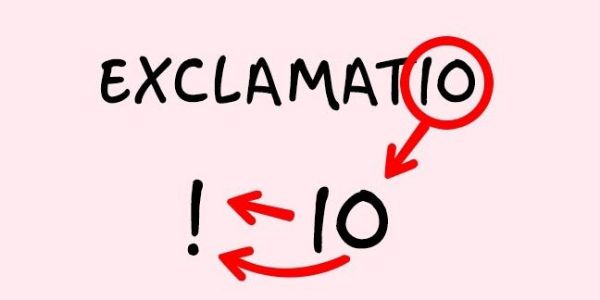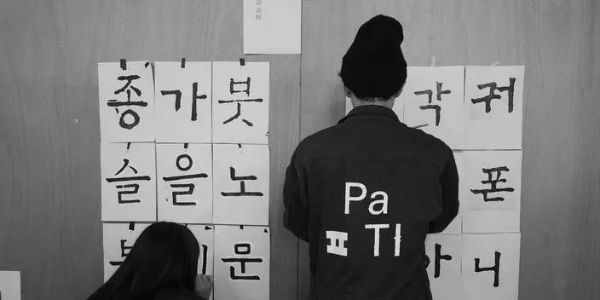
为什么要学字体设计?
为什么要学习字体设计?开年以来还是陆陆续续收到部分字友问的这个问题。今天再和大家分享一下。
不难看出,随着大众审美的不断提高,大家对设计感的追求变得不可或缺,使得“字体”在视觉传达设计中有了一个必要存在的趋势。
在讨论字体设计时,我们先要分清楚字体和字库设计的区别。
字库的设计更多需要注重大范围的可阅读性、辨识性、统一性、推广性,中国字库设计中以六千七百多个字体为一套,可以满足基本的应用需要的,而这样一套的精品字库设计动辄需要半年以上的时间完成,甚至耗时一年两年都有可能。显然,字库设计需要庞大的、系统的团队合作完成,并非所有独立设计师都能有此条件尝试作业。
字库里的字体,常用在句子、短文段落,很难满足个性化的设计需求,这个时候就需要制定的字体设计,它不同于字库设计,制定的字体设计是经过艺术性加工和升华的字体,对比字库中统一、稳定,个性不强的字型,字体设计所展现的汉字结构和图形的魅力更加独特的个性化。
在视觉设计中,几乎都会使用到字体,字体是最基础的设计元素,也是设计中必不可少的表达工具,海报、包装、标志、书籍、广告、影视……甚至在环境设计中都可见字体的应用。字体,除了准确传达信息的基础功能,还需要赋予其美观的形态,使其视觉传达更为强烈与丰富,更能引起用户的注意。
字体设计的应用范围非常广泛,我大致将常见的字体设计应用环境分为:标志、包装、海报、广告、书籍等5大类。为了方便大家理解,我挑选了一些优秀设计师的部分作品和大家讲解一下。另外,文章底部也会和大家说个消息。
有品牌必有标志,标志是品牌的核心象征。就品牌设计而言,字体设计即可作为品牌标志所应用,是图形也是文字。
标志 /
字体的设计可以直接体现品牌的行业的属性。比如化妆护肤品行业,多用纤细优雅的字体,金融类多以刚毅,稳重的字体为主,这样的字体设计可以从潜意识里传达给用户有效的信息,字体中的元素在平面广告、包装、产品,乃至在装潢上的应用,都渗透品牌的形象。
以字体为设计的LOGO,不仅面对的受众更多阶层更广泛,其传播性也更直接。
包装 /
在产品包装上,更是少不了字体设计。字体是包装信息传达的重要视觉元素,精心设计的字体使商品包装魅力十足。
海报/
海报有三大功能,广告、艺术和文化传播。优秀的海报,往往具有很高的设计水准,对图形、文字、色彩等设计元素运用相得益彰,提升视觉表现力的同时又具备独特的艺术魅力。
如果只用字库字体,往往很难达到突出主题的理想效果,这时候就需要设计师,自己动手做字体设计了。那些应景又个性化字体设计,最常见的在影视、游戏、主题活动的海报中。
插画s设计:Mr.PIZZA!
动态设计 n:Wild Design 陳志育 Ida Chen / 吳昱緯 Phil Wu / 侯思妤 Szu-Yu Hou
书籍/
书籍,不能没有字体设计。正文的字体应该遵循阅读顺畅的原则,字体的变化不能过于复杂,文字的排列要符合语言的阅读习惯,以便读者能快速识别。而书籍封面的书名,作为封面首要元素,快速可识别性显得更为重要。字体设计合理搭配色彩,让读者第一时间捕获到的视觉信息,将书名设计为封面首要元素,将有助于读者判断是否拿起书翻阅,从而决定是否购买。
设计师:郭欣翔
《信号Signal :原著剧本》书籍封面设计
设计师:朱陈毅
客户: Faces Publications
设计师:王志弘
随着新媒体的出现,设计的载体也从原来的纸媒到现在的屏幕显示为主。字体作为一个交流的基本途径,它的作用也在发生着变化,字体的变化也越来越多,现在开始出现电商海报、手机主题字体、动态字体、海报,旨在给用户更多的视觉体验和感官享受。
天猫2018双十一
◢诚品书店海报
设计师:Yun-Fang Ho
客户 : The Wall Music / 這牆音樂